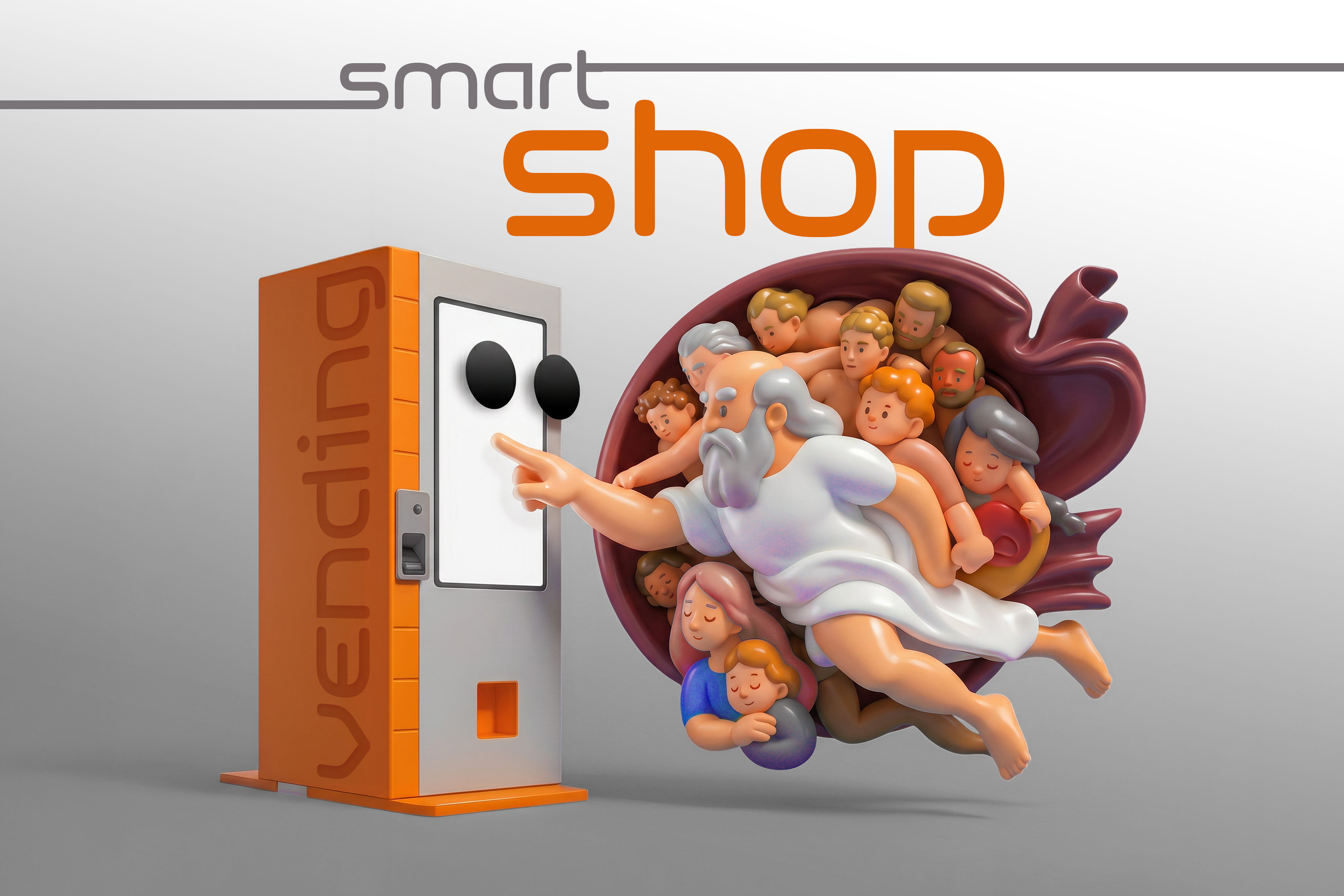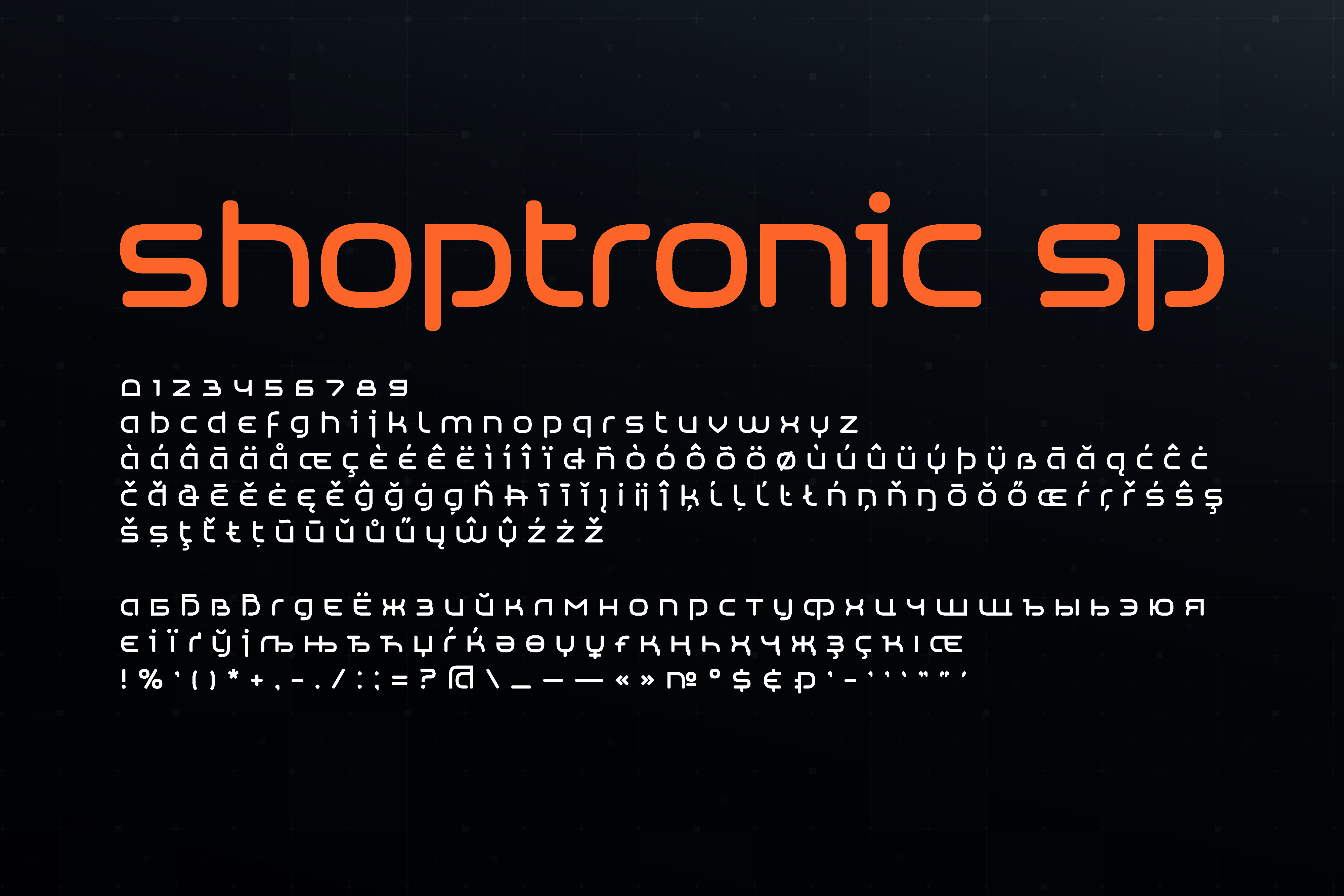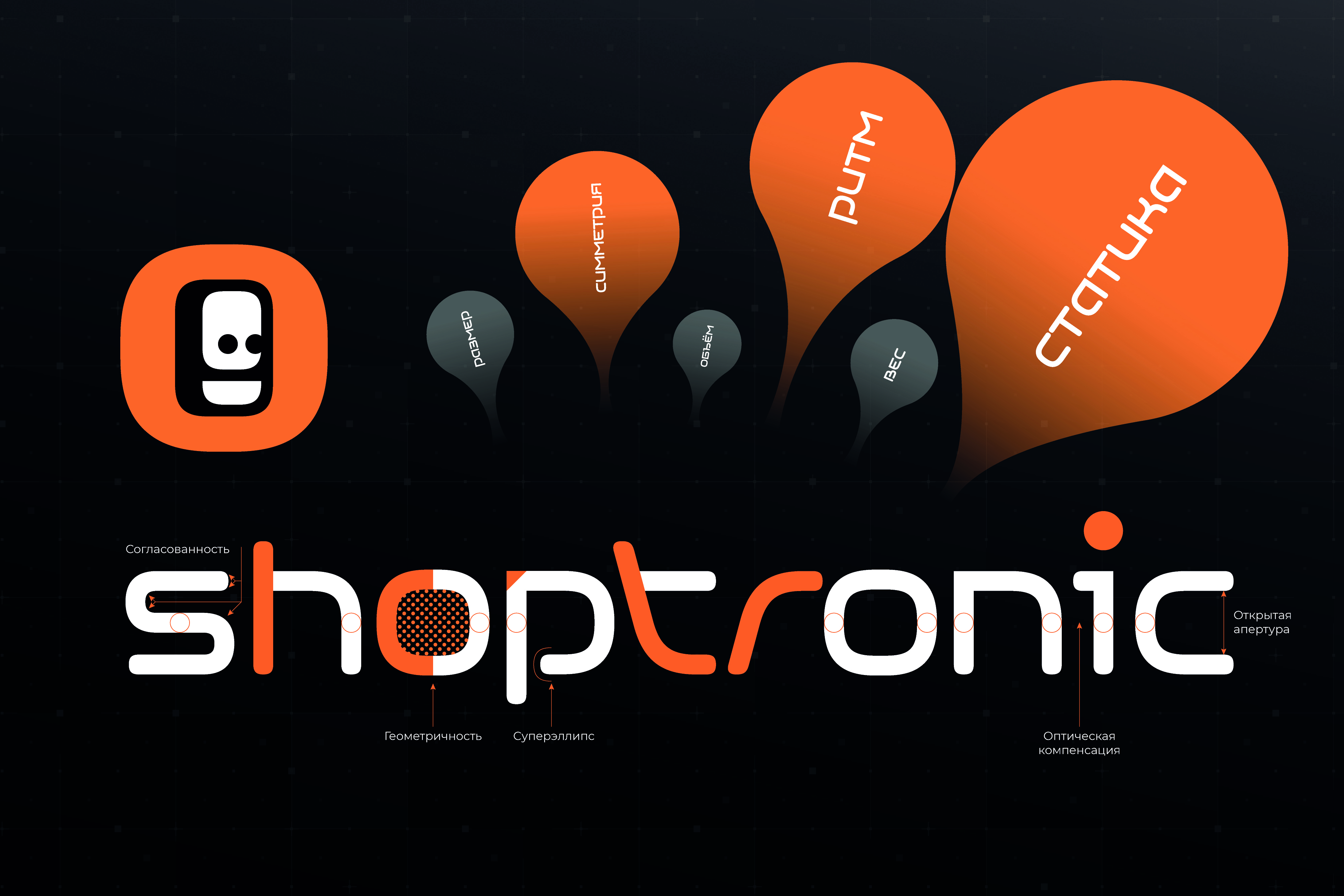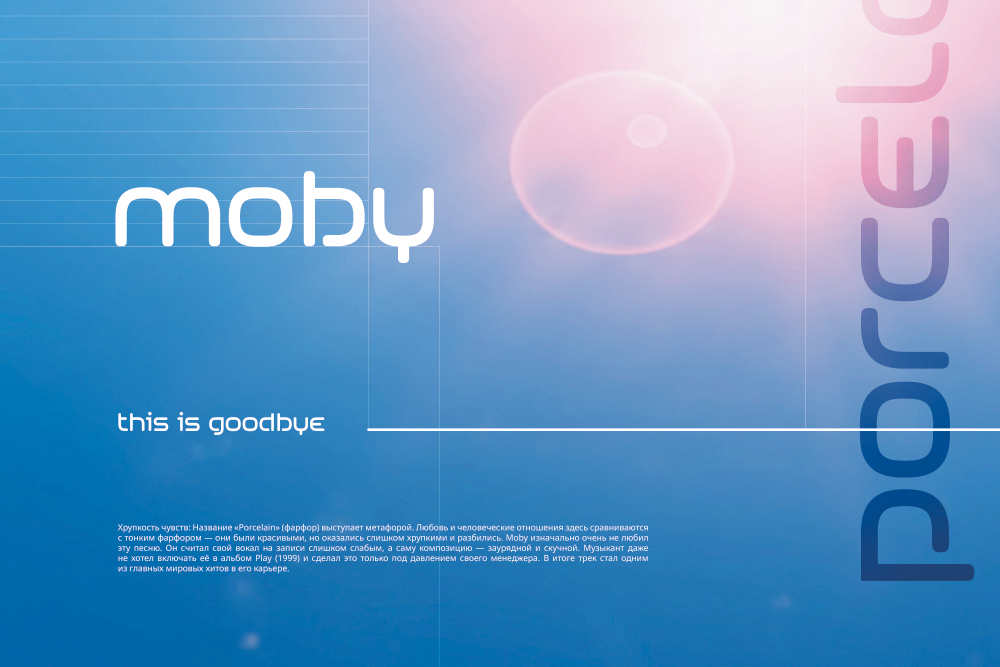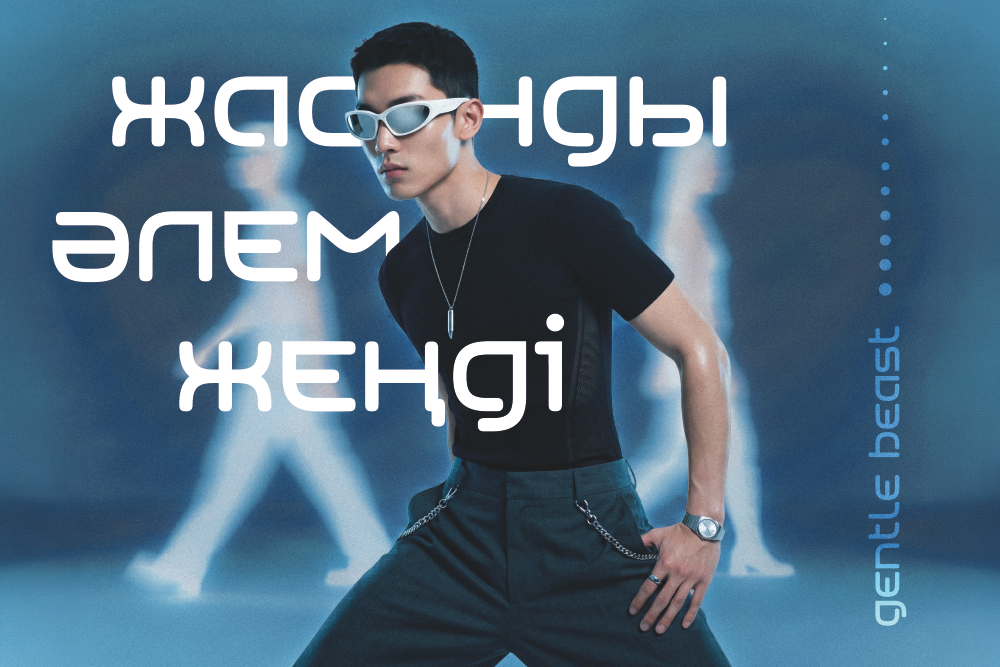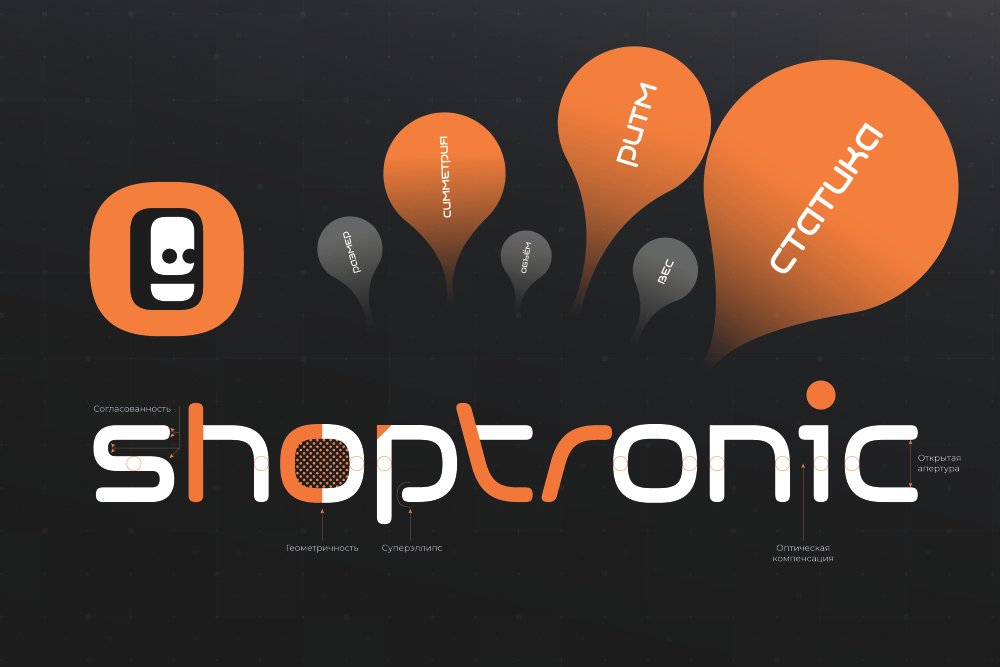
Шрифт Шоптроник
Shoptronic — геометрический гротеск с точным, слегка футуристичным характером. В основе лежит магистерское исследование автора о том, как форма глифов влияет на восприятие: отсюда открытая апертура, согласованный вес штриха и оптическая компенсация узлов. Tech- и fashion-брендинг, музыкальная айдентика, рекламные кампании, интерфейсная графика — задачи, где геометрия не должна выглядеть холодной. В комплекте — полная версия STAR и лицензия.
Акцидентный шрифт